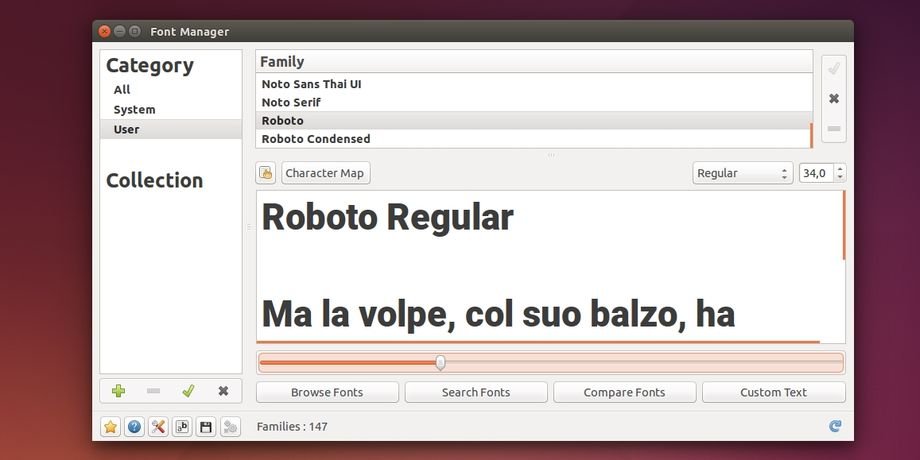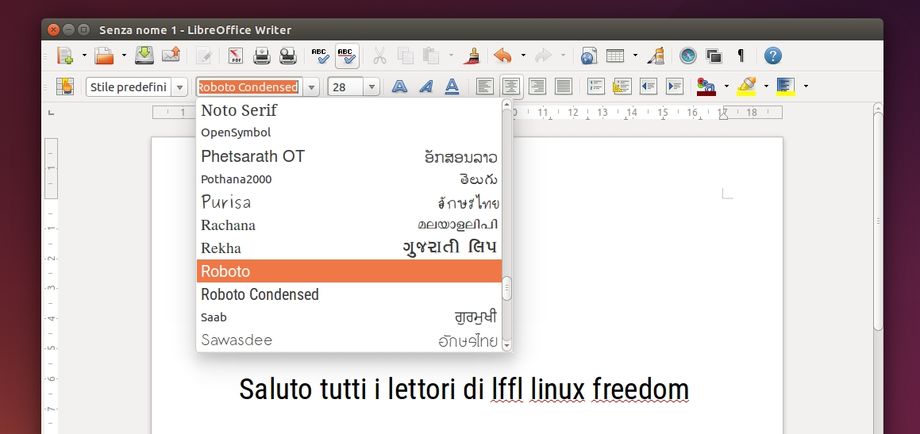
Google ha recentemente presentato il nuovo Android L nuova ed importate release che rende ancora più completo il sistema operativo mobile più utilizzato al mondo. Tra le tante novità incluse in Android L troviamo anche alcuni nuovi sfondi, suonerie, applicazioni come ad esempio la nuova tastiera e anche nuovi font compreso il nuovo Roboto rivisitato per migliore integrazione con il nuovo Material Design. Possiamo utilizzare anche nella nostra distribuzione Linux i tanti nuovi font di default in Android L per creare ad esempio nuovi documenti, migliorare la leggibilità in display di piccole dimensioni ecc.
Grazie alle prime “preview” di Android L possiamo già estrarre font, sfondi, suonerie ecc di default in Android L che possiamo utilizzare anche nella nostra distribuzione Linux. In Android L troviamo ben 98 nuovi caratteri / font che possiamo utilizzare nella nostra distribuzione ad esempio per dare un look più “moderno” si nostri documenti di LibreOffice o AbiWord ecc.